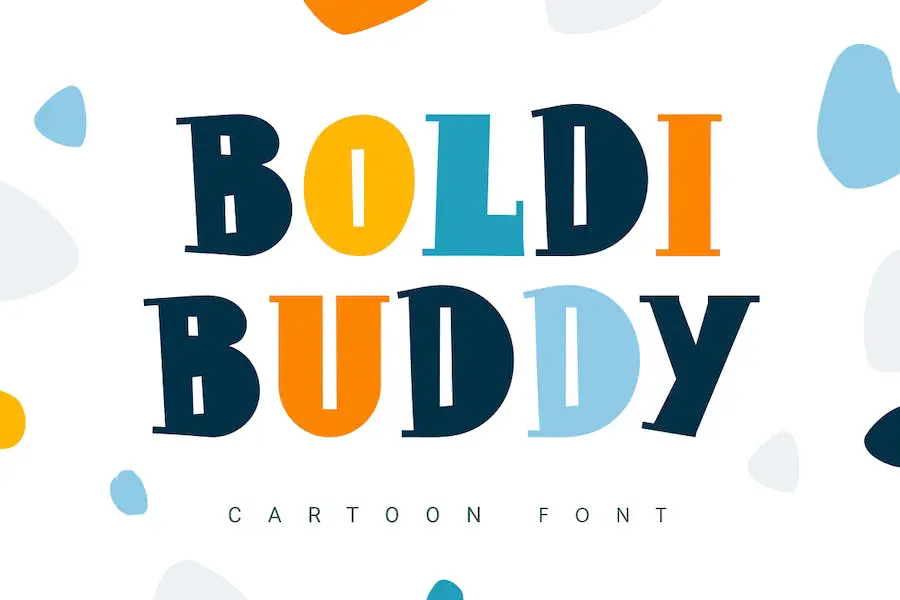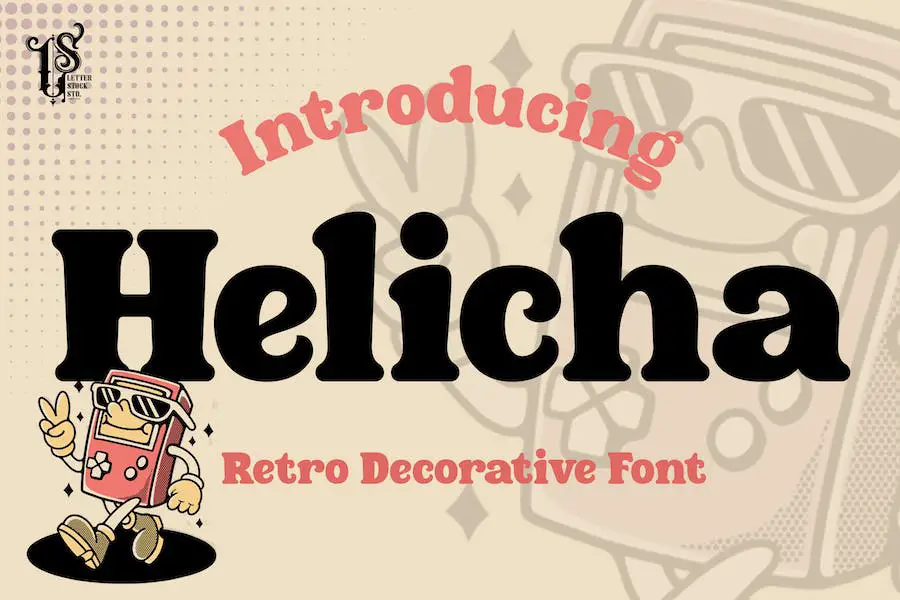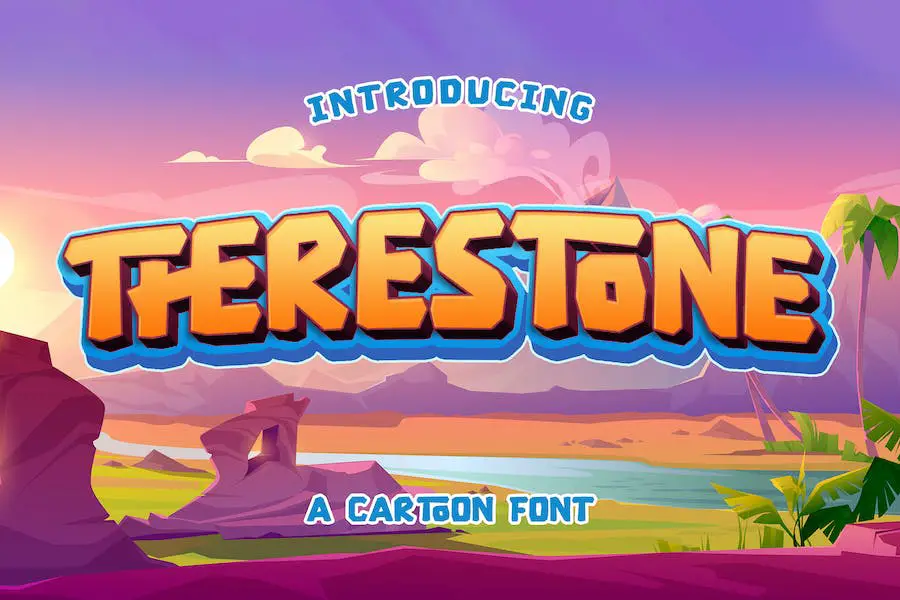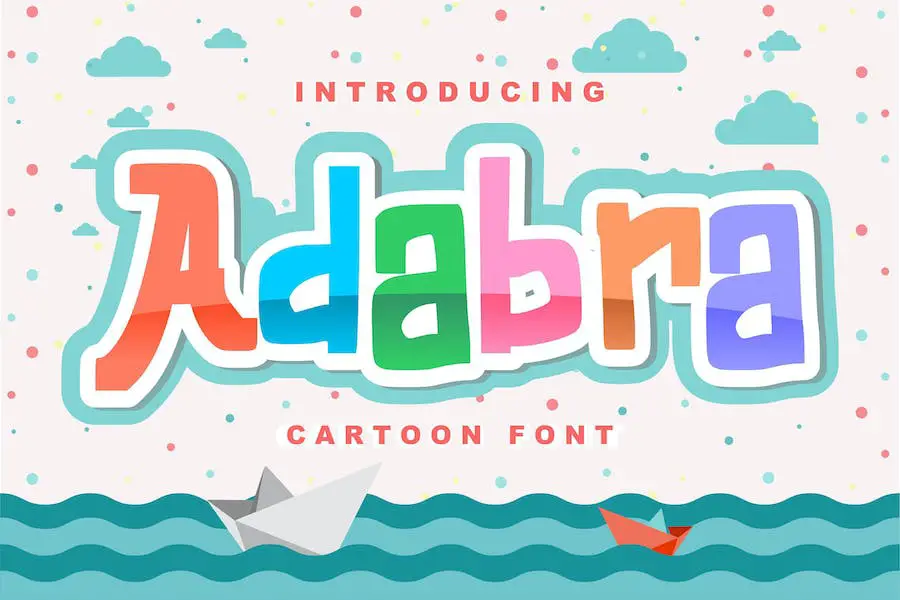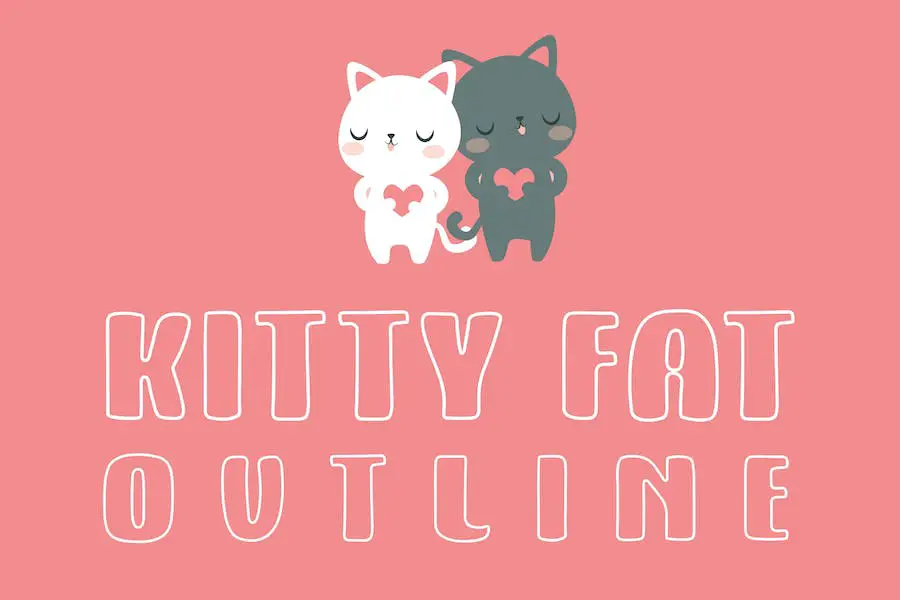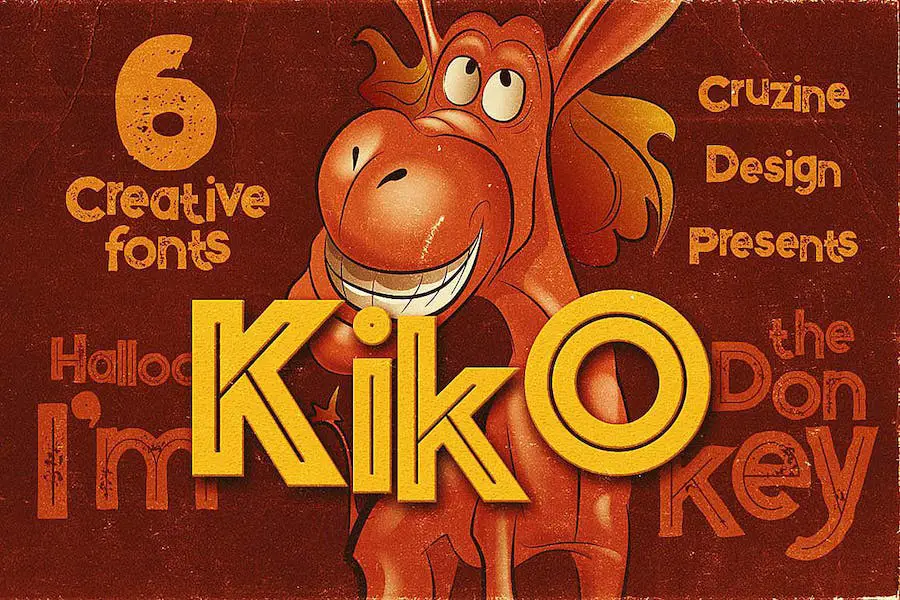
Las 36 mejores fuentes de dibujos animados (cómic, manga y dibujos animados) 2023 (gratis y premium)
Publicado: 2023-07-26¿Alguna vez te encuentras luchando por encontrar la fuente perfecta para dar vida a tus proyectos de diseño gráfico con un toque de fantasía y diversión? ¡No busque más!
En esta publicación de blog, reunimos las 36 mejores fuentes de dibujos animados que, sin duda, elevarán sus diseños al siguiente nivel.
Ahora, es posible que se pregunte: "¿Por qué necesito fuentes de dibujos animados para mis proyectos?" Bueno, los estudios han demostrado que la incorporación de elementos divertidos y atractivos, como fuentes de dibujos animados, puede mejorar significativamente el atractivo general y la eficacia de sus diseños.
Entonces, ya sea que esté trabajando en un libro para niños, un logotipo, un póster o cualquier otro esfuerzo creativo, estas fuentes garantizan una impresión duradera.
Imagine usar una fuente que evoque recuerdos de sus dibujos animados favoritos de la infancia, evocando instantáneamente sentimientos de alegría y nostalgia. Con una amplia variedad de estilos, desde audaces y extravagantes hasta lindos y burbujeantes, estas fuentes de dibujos animados ofrecen infinitas posibilidades para expresar tu creatividad.
Además, son increíblemente versátiles y se pueden usar tanto en proyectos digitales como impresos. Así que prepárate para sumergirte en esta emocionante colección de fuentes de dibujos animados y descubre la perfecta para tus próximos proyectos. ¡Comencemos esta aventura llena de fuentes!
Las mejores fuentes premium de dibujos animados
¿Busca agregar un toque de diversión y nostalgia a sus proyectos de diseño? No busque más allá de nuestra colección de las mejores fuentes premium de dibujos animados.
Estas fuentes seguramente darán vida a sus diseños y cautivarán a su audiencia. ¡No pierdas la oportunidad de ver los siguientes productos y da rienda suelta a tu creatividad!
KOMIKZ
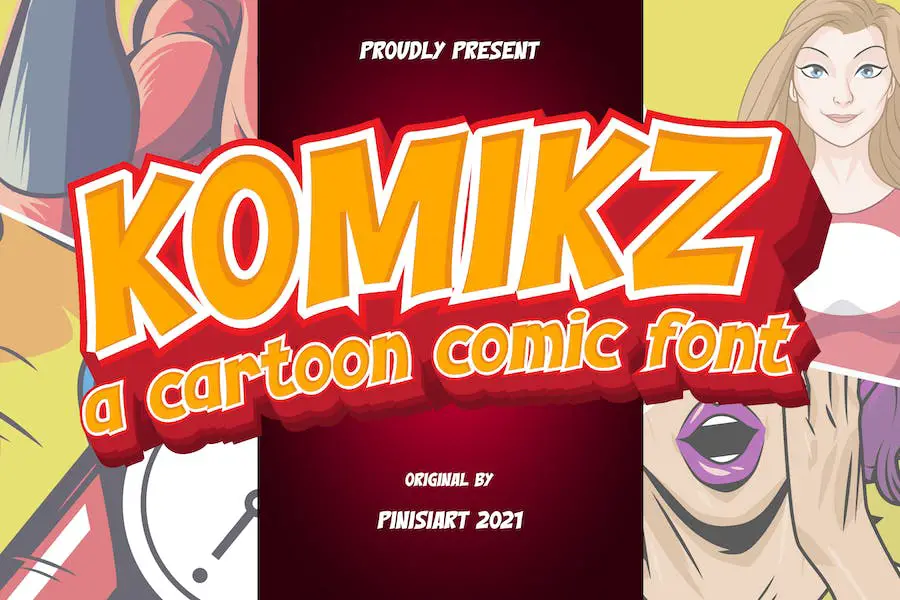
Con KOMIKZ, puede mejorar sus juegos en línea, carteles, títulos de películas, menús de comida rápida, revistas, portadas de YouTube, miniaturas y portadas de páginas de redes sociales.
Yumna
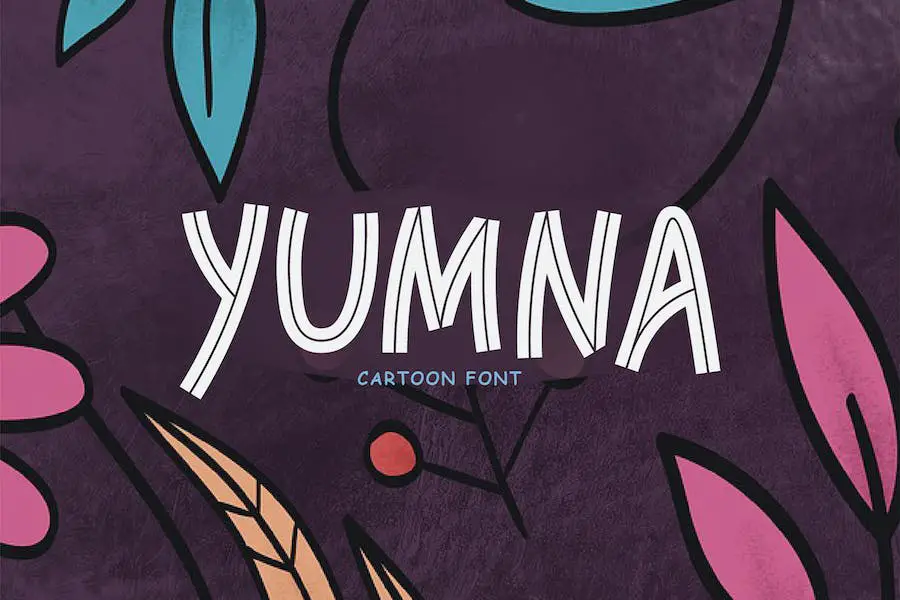
Yumna es una fuente encantadora creada por wap_std que es perfecta para añadir un toque divertido a tus proyectos. Esta linda y divertida fuente es ideal para cómics, diálogos en cómics e incluso manga. Hecho con amor, Yumna traerá una sensación de alegría y creatividad a cualquier diseño.
Con sus personajes lindos y juguetones, Yumna es una excelente opción para los diseñadores gráficos que desean mejorar sus proyectos con un toque de fantasía.
Entonces, si eres un diseñador gráfico en busca de una fuente que aporte un toque divertido y divertido a tus proyectos, no busques más allá de Yumna.
Esta fuente es perfecta para cómics, diálogos de cómics y diseños de estilo manga. Con sus lindos y encantadores personajes, Yumna realzará cualquier proyecto con un sentido de creatividad y fantasía. Pruébelo y vea cómo puede mejorar su juego de diseño.
Kailinasih
Kailinasih es una fuente lúdica que aporta un ambiente divertido y alegre a tus diseños. Perfecta para niños, dibujos animados y cualquier tema divertido, esta fuente seguramente agregará un toque extra de fantasía a sus proyectos.
Con letras minúsculas y mayúsculas, Kailinasih ofrece versatilidad en sus opciones de diseño. También incluye números, lo que lo hace adecuado para agregar un toque divertido a cualquier elemento numérico en sus diseños.
funicornio
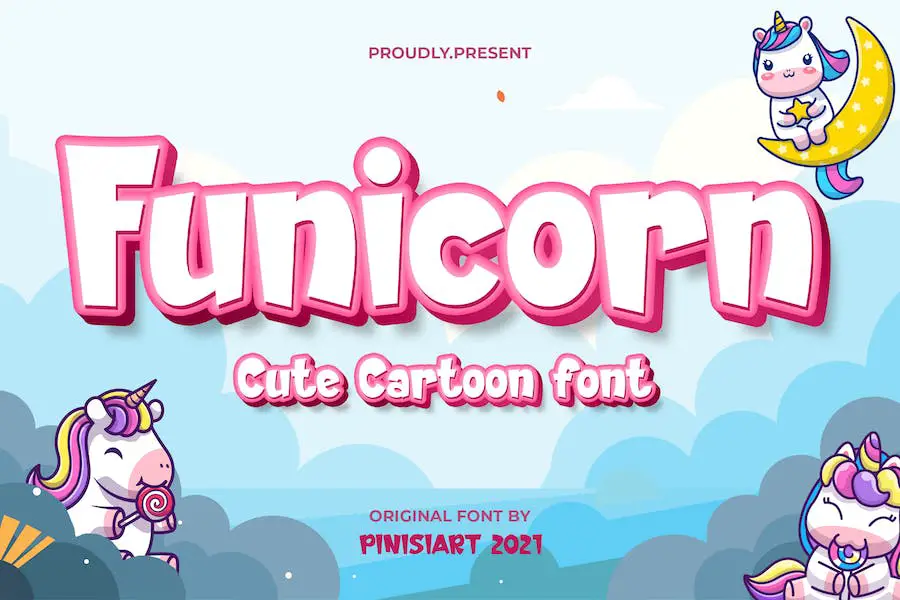
Lo que distingue a Funicorn de otras fuentes es su versatilidad. Funciona a la perfección tanto en PC como en Mac, lo que garantiza que, independientemente del sistema que utilice, podrá disfrutar de sus ventajas.
Con su amplia gama de aplicaciones, es especialmente adecuado para el mercado de libros infantiles imaginarios, juegos en línea, artículos de papelería, útiles escolares, carteles, títulos de películas, portadas de YouTube, miniaturas de YouTube y portadas de páginas de redes sociales.
Vida acuática
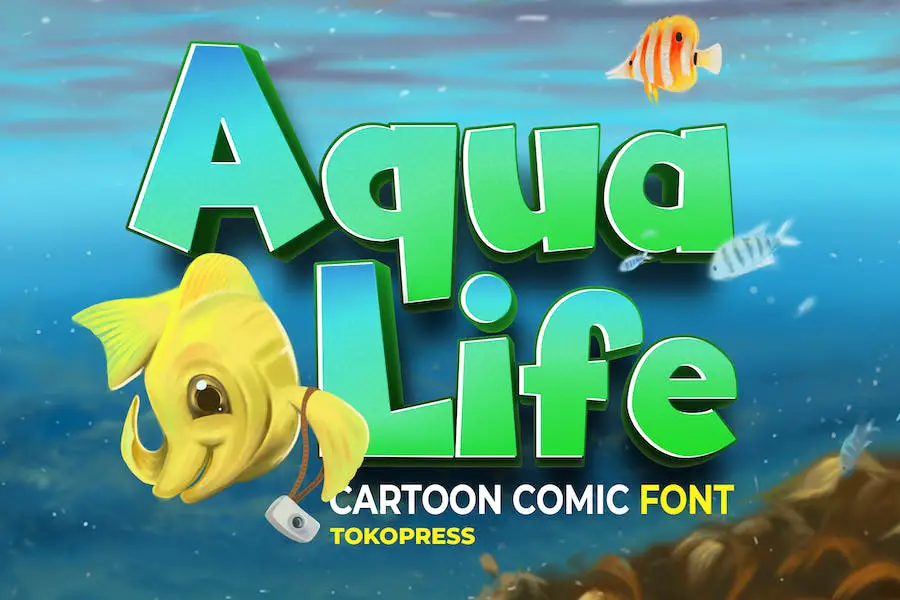
Aqua Life es una fuente que trae felicidad y alegría al mundo de los niños. Tiene el poder de hacer sonreír a las personas y es totalmente accesible sin necesidad de software de diseño adicional.
Con una variedad de caracteres que incluyen latín básico, números y puntuación, Aqua Life es perfecta para crear historietas, manga y anime, y cualquier proyecto que requiera una fuente para diálogos de historietas.